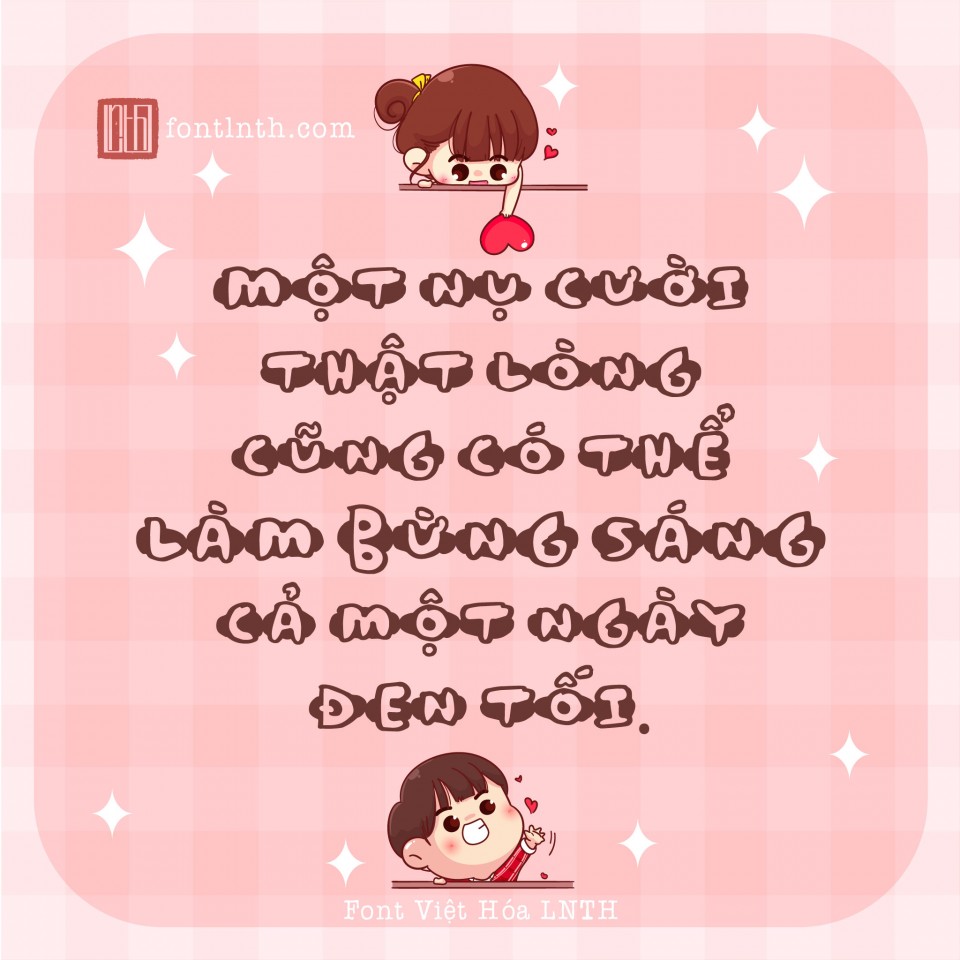
Font việt hóa LNTH Chicken Waffles
Font việt hóa LNTH Chicken Waffles – Nét chữ sáng tạo cho thiết kế học đường
Giới thiệu về Font việt hóa LNTH Chicken Waffles
Trong thế giới đồ họa hiện đại, việc lựa chọn một Font Miễn Phí phù hợp đóng vai trò quan trọng trong việc truyền tải thông điệp. Font việt hóa LNTH Chicken Waffles là một bộ phông chữ mang phong cách vui nhộn, năng động và tràn đầy năng lượng. Với các đường nét tròn trịa và mềm mại, bộ font này mô phỏng lại sự ấm áp của những món ăn sáng quen thuộc, giúp các ấn phẩm thiết kế trở nên gần gũi và thân thiện hơn với người xem, đặc biệt là các bạn học sinh.
Ưu điểm nổi bật của Font việt hóa LNTH Chicken Waffles
Thiết kế độc đáo và linh hoạt
Font việt hóa LNTH Chicken Waffles nổi bật nhờ cấu trúc chữ dày dặn nhưng vẫn giữ được sự thanh thoát. Sự biến tấu trong các nét chữ tạo nên một nhịp điệu hình ảnh thú vị, giúp các tiêu đề bài giảng, bìa báo tường hay các dự án ngoại khóa trở nên sinh động. Độ tương phản thấp của font giúp người đọc không bị mỏi mắt, đồng thời tạo ra cảm giác thủ công rất chân thực.
Khả năng ứng dụng đa dạng
Không chỉ giới hạn trong môi trường học đường, bộ font này còn cực kỳ hiệu quả khi áp dụng vào thiết kế menu quán cà phê, bao bì sản phẩm hoặc các thiệp chúc mừng. Nhờ việc tối ưu hóa tiếng Việt hoàn chỉnh, người dùng có thể sử dụng các dấu thanh một cách chuẩn xác mà không lo bị lỗi hiển thị hay mất nét, đảm bảo tính thẩm mỹ cao nhất cho mọi sản phẩm thiết kế.
Hướng dẫn sử dụng và kết luận